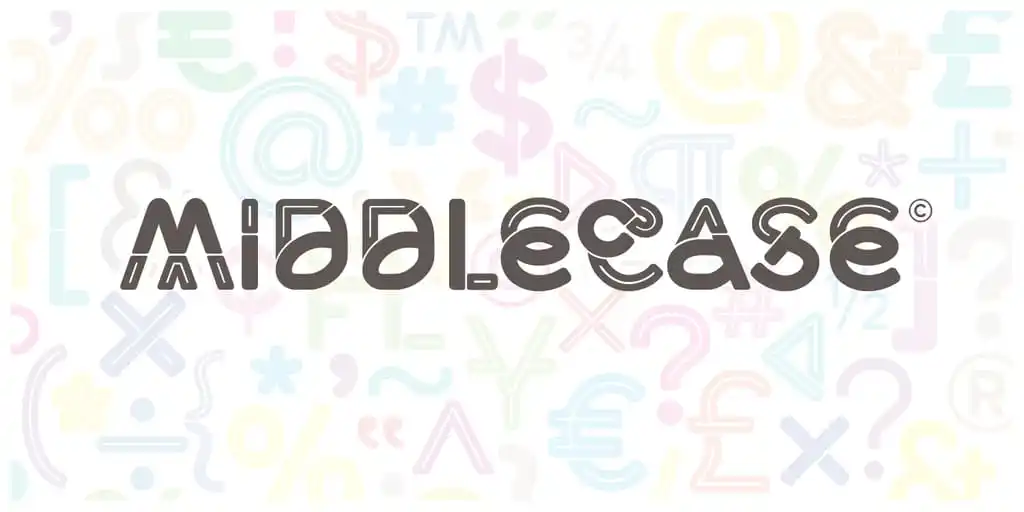
A fonte Middlecase é uma experimentação inovadora do designer Morice Kastoun, que junta as formas maiúsculas e minúsculas num conjunto único de caracteres. Uma ideia radical que desfaz os limites entre a classificação dos casos de fontes e o que está possível no design de fontes. Middlecase é uma opção única para aqueles buscando algo realmente diferente e inovador, certamente destacará seu trabalho ao invés de sumir no pânico visual da multidão. Esta fonte é perfeita para quem quer imprimir uma marca ou criar um layout que seja mais chamativo sem perder a legibilidade. A experiência do usuário foi cuidadosamente pensada para garantir que você possa trabalhar com ela sem problemas, tornando-a não apenas uma versão de escritório da fonte, mas também uma opção versátil e divertida para aplicativos digitais ou impressos.